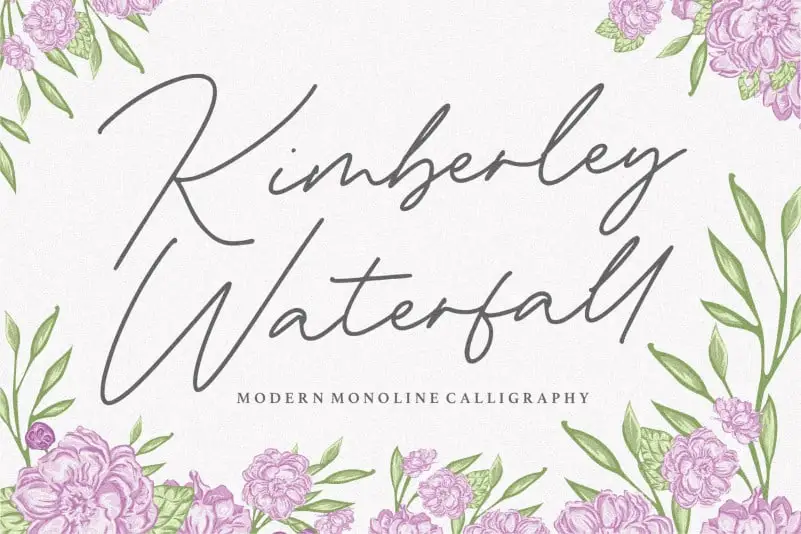
Kimberley Waterfall Monoline Calligraphy Font – Download Grátis
Prestes a desfrutar de uma experiência única no mundo das fuentes para escrita manuscrita, apresentamos Kimberley Waterfall Monoline Calligraphy Font, criada pelo talentoso designer balpirick. Esta fonte é mais do que um simples conjunto de letras digitais; ela oferece uma sensação natural e envolvente que se encaixa perfeitamente em qualquer projeto gráfico ou design de escrita manuscrita. Com seu estilo monoline, Kimberley Waterfall captura a essência da escrita manuscrita tradicional, proporcionando linhas finas e uniformes que destacam as características únicas dos caracteres. Suave e elegante, esta fonte é ideal para qualquer projeto que busca um equilíbrio entre modernidade e elegância. Ideal tanto para uso em materiais impressos quanto para criação digital, Kimberley Waterfall oferece uma solução de escrita manuscrita única e incrivelmente natural. Quebre o padrão e explore a paleta de estilos disponíveis para encontrar a fonte perfeita que irá complementar seus projetos de forma maravilhosa. Estamos ansiosos para que você descubra os benefícios desta fonte exclusiva, uma vez mais, assim como milhares de outros usuários já fizeram. O Kimberley Waterfall Monoline Calligraphy Font é um investimento que trará tanto valor quanto criatividade ao seu trabalho.